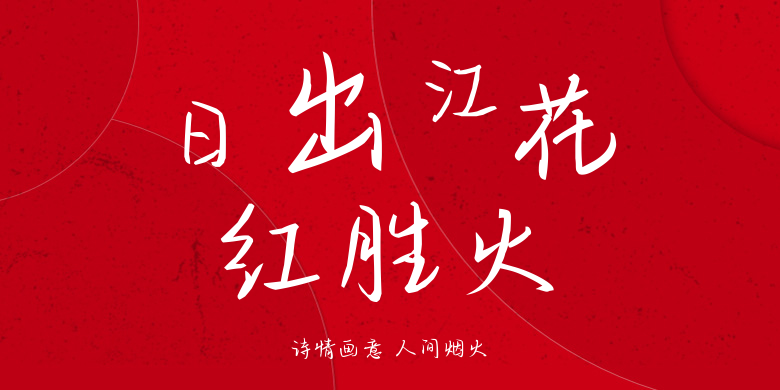
诗情画意 人间烟火
诗情画意 人间烟火,这款字体结构工整、笔画清晰,兼顾美观与易读性,适用于标题、正文、海报、包装、LOGO 等多种场景。字形优雅稳定,风格百搭耐看,适配日常排版与创意设计,让文字呈现更舒适、更具质感。诗情画意 人间烟火一笔一画,皆是细节,以均衡的比例、流畅的线条打造舒适视觉体验,字形端正大气,风格简约现代。无论是商业设计、品牌宣传还是日常排版,都能轻松驾驭,让文字更有格调与力量。诗情画意 人间烟火字体下载。